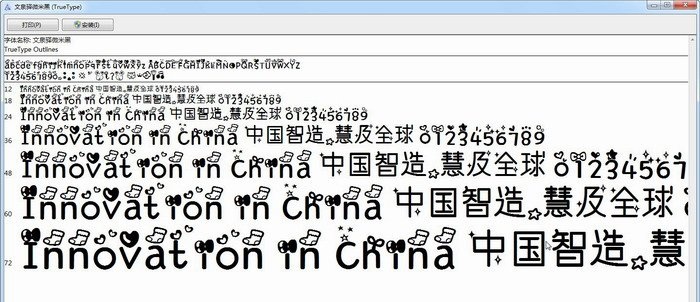
卡通愛(ài)情字體是一款專(zhuān)門(mén)為用戶用于蝴蝶結(jié)設(shè)計(jì)的字體,讓你快速設(shè)計(jì)圖案等必備字體,有需要的用戶歡迎下載!
以黑體為原型,在字體間嵌入大量的卡通圖案,標(biāo)點(diǎn)也換成了卡通圖案
即具有黑體的端正易認(rèn)風(fēng)格,又很有趣味性
以獨(dú)特的手寫(xiě)風(fēng)格和俏皮的樣式,使字體看起來(lái)更加的個(gè)性時(shí)尚。